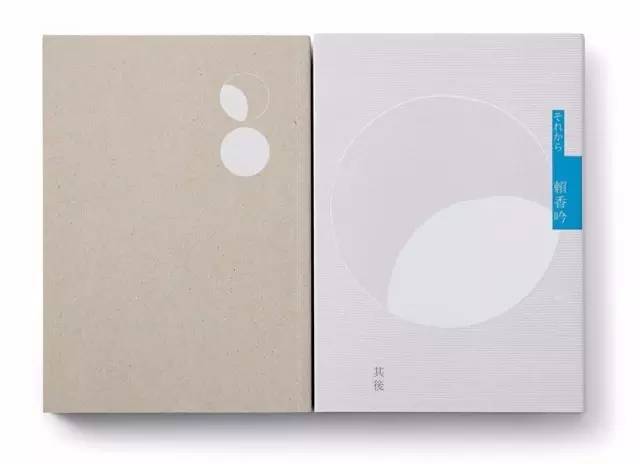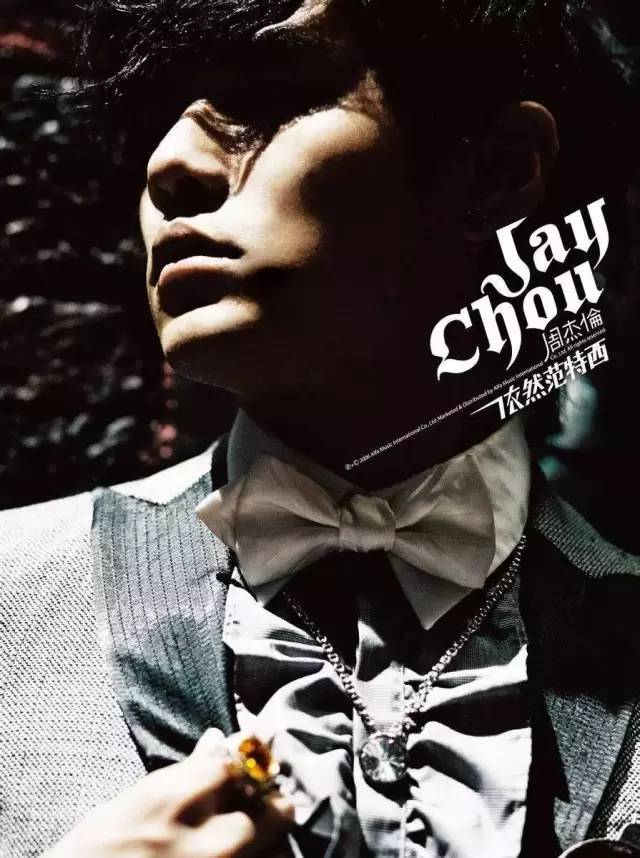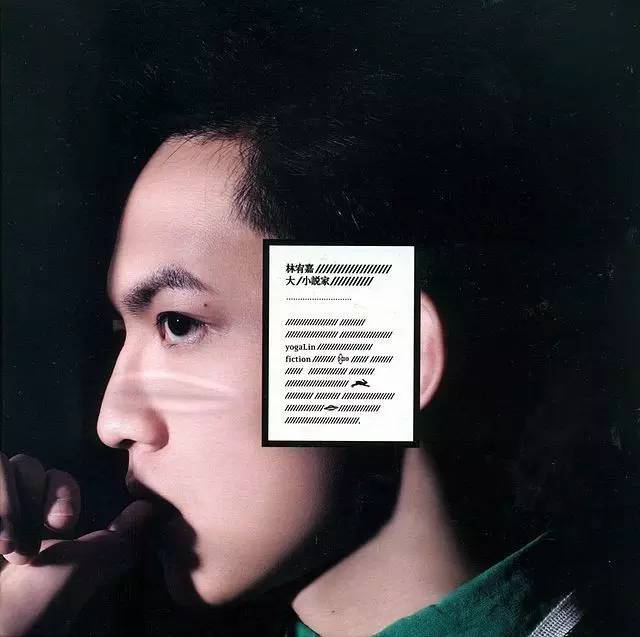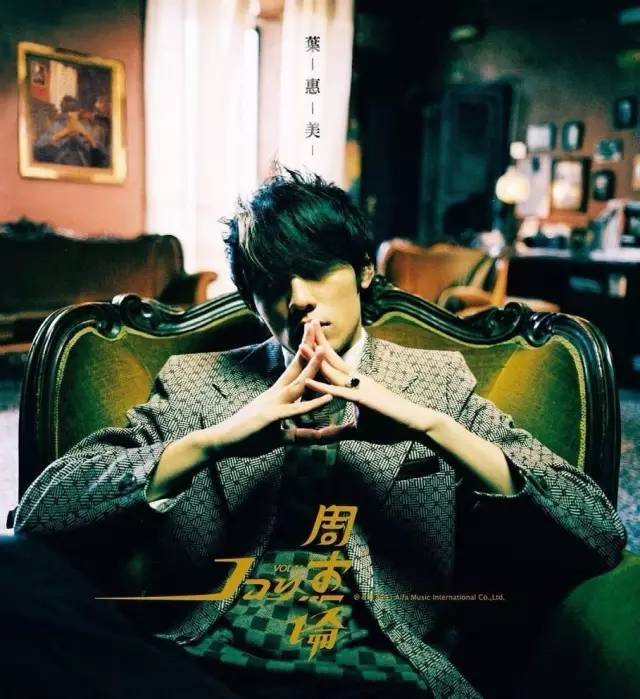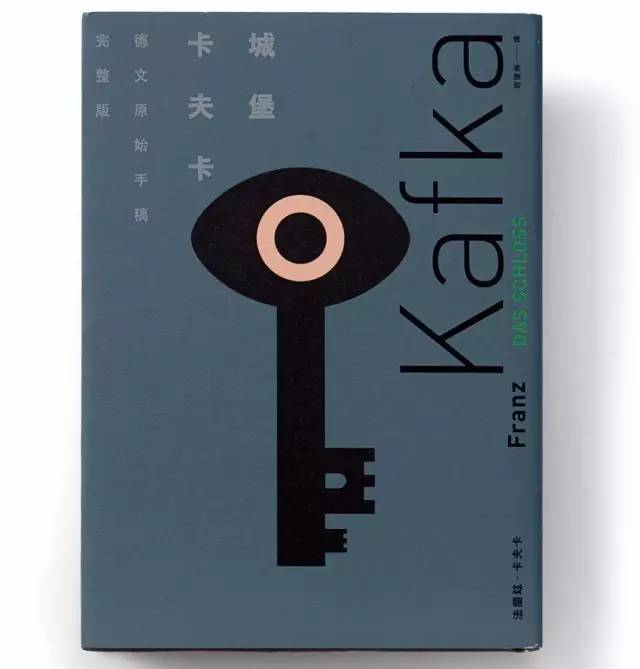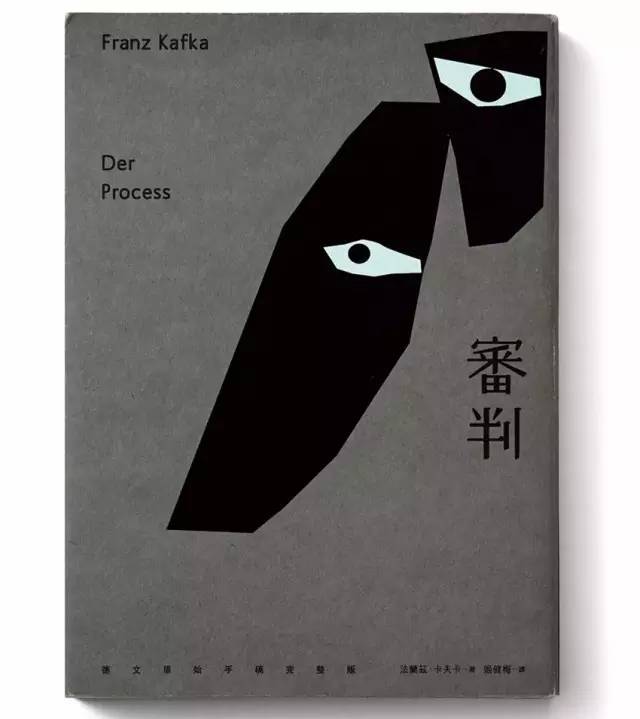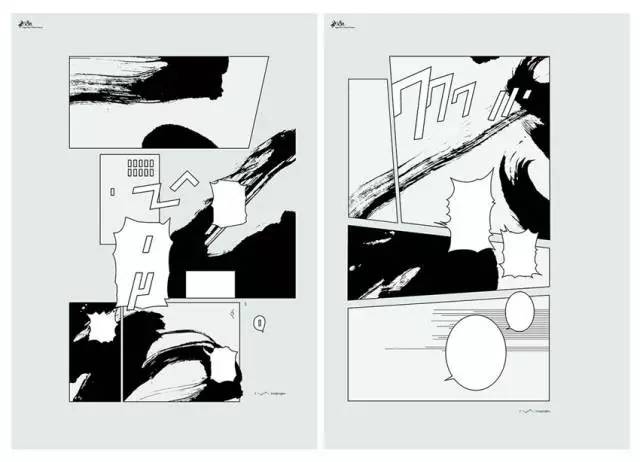
他是周杰伦御用设计师,对不美的绝不妥协!
聂永真,台湾著名设计师。
独揽华语乐坛唱片设计70%的市场,他是目前华语唱片设计你不能不知道的一号人物。
比想成名更早成名的人
大二那年,聂永真参加第一届诚品创意文案比赛,一举获奖,自此成为诚品商场的特约文案,之后被唱片界「钦点」,为张惠妹、周杰伦、五月天、林宥嘉等歌手专辑做视觉包装,帮各家出版社做书籍装帧 ,为两厅院展演、金马影展做海报设计,得奖从来是常见的事。
起步早,成名早,聂永真的名字总出现在质感很好,名气很大的出版品上面,于是,聂永真不可避免地成为「设计明星」。每隔一段时间,聂永真的名字就要在新闻上出现,媒体用「在平面设计界投下一枚震撼弹」来形容他成为AGI会员,不论是以35岁进入AGI或是第一位台湾会员,聂永真显然为台湾设计界写下了新记录。
广为设计人所知的AGI,在1951年创立于法国巴黎,自创会起,即每年轮流在世界各地举行年会,并进行学术探讨与举办会员作品展览,1969年起AGI总部从巴黎移至瑞士的苏黎世。AGI成员都是全世界优秀及有影响力的设计师,因此在国际间享有崇高的地位,被视为国际平面设计界的「殿堂级组织」。
AGI入会门槛高,每年仅接受极少数的新人,且须先由三位会员函信署名推荐,再通过七成以上AGI委员会学术评审同意,历年铩羽而归者众。聂永真坦言,即使有人推荐,自己也认真把作品都整理好了,但是把资料寄出去之后,就又回到正常生活了,因此听到恭喜电话时,聂永真说:「很激动,简直快疯了。」
然而进入AGI,对个人的最大意义是什么?聂永真直率地说:「以往不论在作品上有多努力,得过多少奖,还是免不了会被嘲讽,是因为做了很多明星的唱片才成为沾了光的人。」成为AGI会员,某种程度上是一种证明,也许嘲讽的声音还是会出现,但是自己好像有了防护罩一样,不会那麽在意了!
不想当“周杰伦御用设计师”
聂永真更在意他的“小思考”
起步早,成名早,聂永真的名字总出现在质感很好,名气很大的出版品上面,于是,聂永真不可避免地成为「设计明星」。
对于类似“周杰伦御用设计师”这样的头衔,聂永真有点无奈,“我不希望带给别人‘靠消费这些歌手而成名’的观感”。
部分唱片设计作品欣赏:
▲ 2003年 《叶惠美》专辑設計第一次参与设计周杰伦专辑 (留意字体设计)
聂永真回亿起那时接到周杰伦所属的阿尔法唱片公司打來的邀请设唱片封面的电话,“近乎缺氧的兴奋,在家里忍不住大笑和狂奔”。
▲ 陶喆 ─ 六九乐章,唱片设计
《聂永真:对不美的绝不妥协》
我已经做了13、14年的设计师了,由于我都做很多的主流唱片,但是我自己非常喜欢非主流唱片的东西,所以我一直试着能够有机会,如果自己有更强更多的设计师的诠释权跟话语权的话,我一直希望在我接的这些客户的案子里面,加入很多独立性的东西,很非主流的东西。
我觉得这个事情很重要,如果你做非主流唱片,做这些事情,其实是非常理所当然,没有什么了不起的。但是你今天做的是主流唱片,我觉得主流唱片有一个很好的地方,它的传播层面非常非常的广,传播的方式也非常的快。如果你自己喜欢很特别的东西,既有主流唱片常进去,然后把它发出来,我觉得对这个环境的品位是很有帮助的,所以这几我一直锻炼试着自己做非主流的东西,有一些自己个人的喜好,把自己的很多实验性的东西加进去。
我知道更多比我更厉害的人
一直以来,媒体总是把萧青阳,王志弘,聂永真绑在一起,称为平面设计界「三大天王」,聂永真认为,我们之所以被知道,是因为作品(书籍唱片)都可以看到名字的缘故,这是传播业的特性,但无形中影响了很多设计科系学生,会对这个工作产生浪漫的想像,被定型在某一个「误以为氛围很好的区块」,这显然不是设计应有的良性发展,视觉设计这个领域如此宽广,有更多商业设计作品,虽然不会被标示出设计者的名字,但其实仍有非常好的发挥。
但名气很大,是好事?或是坏事?聂永真直率地说,每次听到人家喊他大师,就觉得很恶心,虽然对自己的作品有自信地说「我知道我很厉害」,但是也知道「还有很多更厉害的人」,自己哪里称得上是大师辈份,但是面对这些有名气带来的影响,聂永真平淡地说,做设计,拿出来的作品才是最重要的!
但即使拿到AGI通行证,聂永真准备出席今年在伦敦的年会,还是得硬着头皮筹旅费,做设计,再出名,也不是随便就拿得出几十万的手笔,筹措经费之初找不到相关的研讨会补助项目,原因是官方没有这类「参加研讨会的预算项目」,一波三折,还好后来得到品牌赞助、以及文化部门的活动合办支持,总算解决了眼前的问题。
部分书籍装帧设计欣赏:
▼九歌的散文、小说选
▼賴香吟《其後》
赖香吟的《其后》是一本很哀伤的、彷彿是病房中的告解的一本书,所以联想到「月阴」,而赖香吟的文字又是很乾淨、无尘的,于是以「白色的月阴」来呈现。
▼卡夫卡《审判》《城堡》
卡夫卡的书不好卖,主要设计诉求就是「有意义的、有卖相的」,以简单的意象来传达,希望年轻人会被封面吸引,进而买回家尝试阅读。
▼恰克•帕拉尼克《斗阵俱乐部》
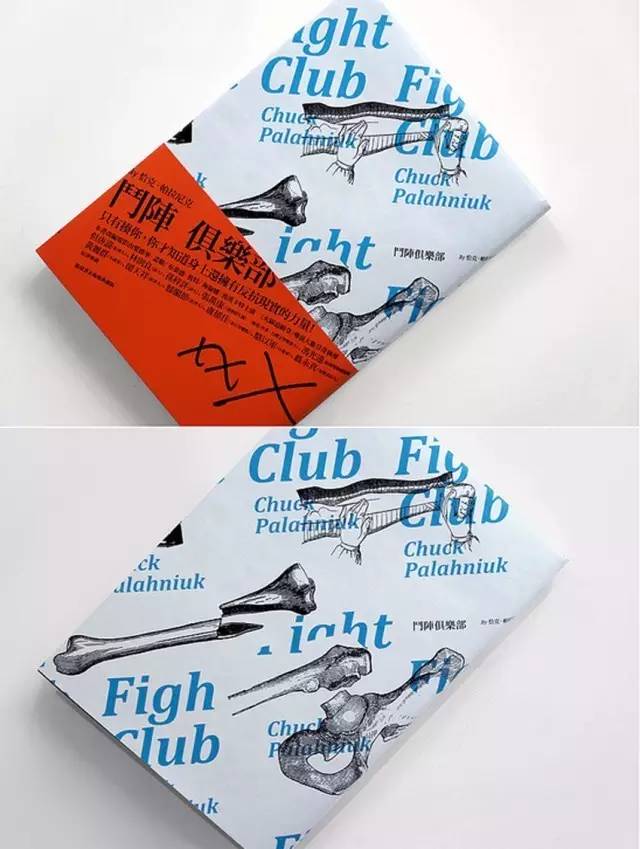
经纪是一件严肃的事
从大学时期就出名,对聂永真的直接影响是,他一毕业就成为freelancer,后来为了业务需要开发票才成立工作室,这显然又是让设计专业学生心生向往的成功案例,但聂永真可没这么浪漫,他建议「任何人在开工作室之前,最好先去其他地方磨练!」
聂永真强调,很多人会沉醉在「自己真的很好的状态里」,但100人当中,其实可能只1人是真的好到可以独立出来就能大红大紫,其他99人也许也不错,但是「没有好到和别人有很大的不同,好到足以被放大或看到」,因此即早认清现实,绝对有助于未来的设计生涯。
早成名或许不难,但要持续成名,恐怕就得有两把刷子!聂永真表示,设计行业被关注的是作品,要面对的是客户,因此只要设计保持水准就够了,其他的事都不必多想。虽然成名的时间点很重要,对设计者来说,有其正反两面的影响,因为成名很容易,但掉落也很容易。
聂永真认为,自己之所以持续被媒体关注,一方面是出版个人作品,加上他是少数有经纪约的平面设计人,合约内容与个人创作有关,许多新闻议题或媒体访问,都可以交由经纪公司处理,自己可以更专心做设计或创作。笑说虽然无法为自转星球(经纪)带来太多利机,但是至少形象正面。
对聂永真来说,良性经纪的定义是,经纪人与被经纪标的都有加分效益,双方是很严肃的合作伙伴。但是如何评估签经纪约的时间点?聂永真则强调,第一个作品要好,人要有自己的显著特质,设计师要具备让经纪「看上」的排众及合作条件,也不该把经纪视做名气操作的工具或目标。
其它设计:
▼No.223攝影集 leaflet
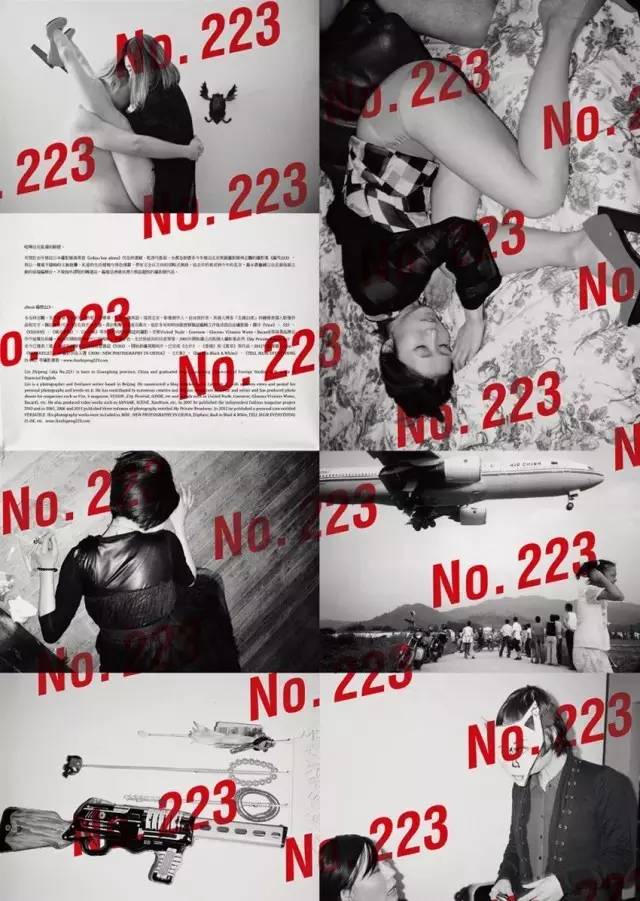
▼第50届金马奖视觉形象设计
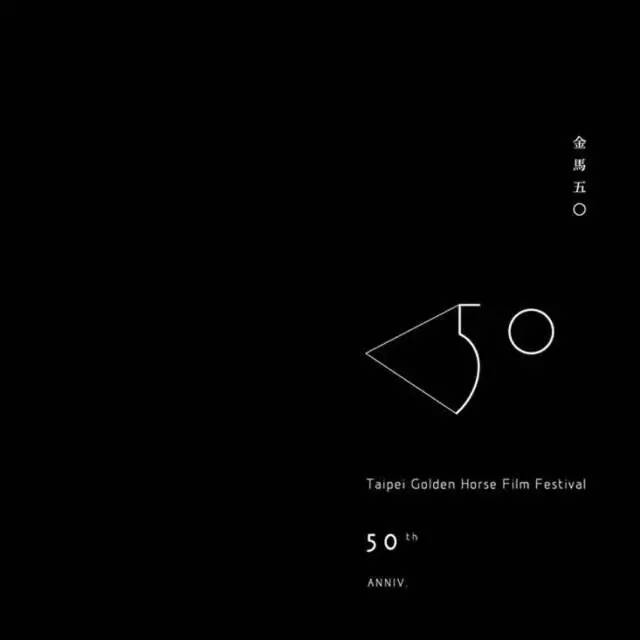
▼海报设计/董阳孜《I See Languages》
我把这个海报的系列称为”I see languages” ,中文叫”看见语言”。其中一组是漫画的对话框,对话框格中的文字内容放上书法的笔触。我把它定义成现在看到这些对话框裡的”对话”有可能会是另外一个星球、一个我们完全不理解语系的语言。会不会有某一种语言表现出来的文字是长这样?所以我抛出来的议题是说,我们没有看见这些符号并不代表这些符号语言不存在,也许我们看的这些笔触,其实是在某个不知名的行星里面的某一个语系的编码系统呢?
另外一组是在看过董阳孜老师的书法字后,我自行将之转换而成的抽象画面。这幅虽然没有看到她书法的痕迹,但还是保留了水墨的感觉。整张海报结合与简化书法的元素而成(红色矩形符号,也就是书法中经常出现的落款),对我而言,就是书法。最后一幅也是,上面的螺丝钉代表某一个符号的编码,选择放螺丝钉这个元素是因为我手上有刺螺丝钉的刺青,它的意义就是代表我。我们活在当下,无法想像未来的各种可能性;也许书法可以被机械化、未来化、符号化,也许以后的平面设计就会被解码或是编码成这样子。
永远往上一阶走的设计路
当聂永真成为「设计偶像」,一定会有很多人解构聂永真的作品,想知道他习惯用哪些梗,「聂永真风格」又是如何被形成的?聂永真表示,每一个好的设计师,都有自己最喜欢的,处理文字大小的字距行距,最喜欢的字型,在版面上的构成方法,对我来说,那不是风格,是技术,风格这两字是最笼统的形容,因为找不到更适合的字了,(这和动不动就称设计人为大师差不多),所以,我自己最重视的是「气」,或者近似灵魂的意思,每位设计者的作品,「气」都是不一样的,对我而言,排得好看是技术可以做到的,但是接下来整体表现的「气」,就是个人的质感特性,举例来说,同样十六页的内容,每一位设计师的表现方式就会不同,每个人把图文安排的位置不一样,就好比编曲,每位的节奏强弱会不一样,我很在意整体节奏的起承转合,这或许又牵涉到个人的喜好度,但是以出版品来说,翻阅的过程有「舒视」的质感,是很重要的!
当被问到,知名度高,在与客户之间的沟通,是否具有相对主导性?聂永真说,做设计,本来就是要建立在明确的市场方向,依据来自客户或企划端备足的条件,可以掌握精确传达的讯息,在客户整理好的脉络之下,其他就是我可以发挥的范围,我认为这是专业分工。设计毕竟和创作不一样,即便可以让设计看起有创作的自由度和艺术性,但背后一定夹带非常精密的计划和市场方向。对聂永真来说,设计的艺术性很重要,他认为,把设计做好是很基本的,或许每个人要考虑的条件都不一样,未来他想做更抽象或觉得自在的作品。
不可讳言,台湾是高度标签化社会,某种意义上,得奖正好迎合了标签化社会的价值观,尤其设计这个行业也有很多不同圈子,很多人会以这个人得到哪些奖项来区分,比如得到红点或IF,但台湾有许多具有大师地位的人,或许一生都没有参加过这些奖项,参赛得奖,对聂永真而言,代表的意义会是什么?
聂永真说,最初并没有太多想法,反正很多人拿到了,我也去报名看看,但到了AGI,意义就大为不同,一想到自己的作品会和这些「很厉害的人」放在一起,这是很大的激励,但也是很大的压力,因为会希望确保自己的作品真的和别人放在一起,也不会太难看,因此就会希望在设计工作之外,也可以留时间给自己去做更自由的创作。
问聂永真,对他个人而言,设计的「再上一阶」在哪里?
聂永真认真的说,AGI看似至高,但自己是Tokyo TDC (东京字体指导俱乐部是极具影响力的字体设计研究团体)的脑残粉,作品再多进一点会更有益自己的心理健康(聂永真之前已入选过多次)。